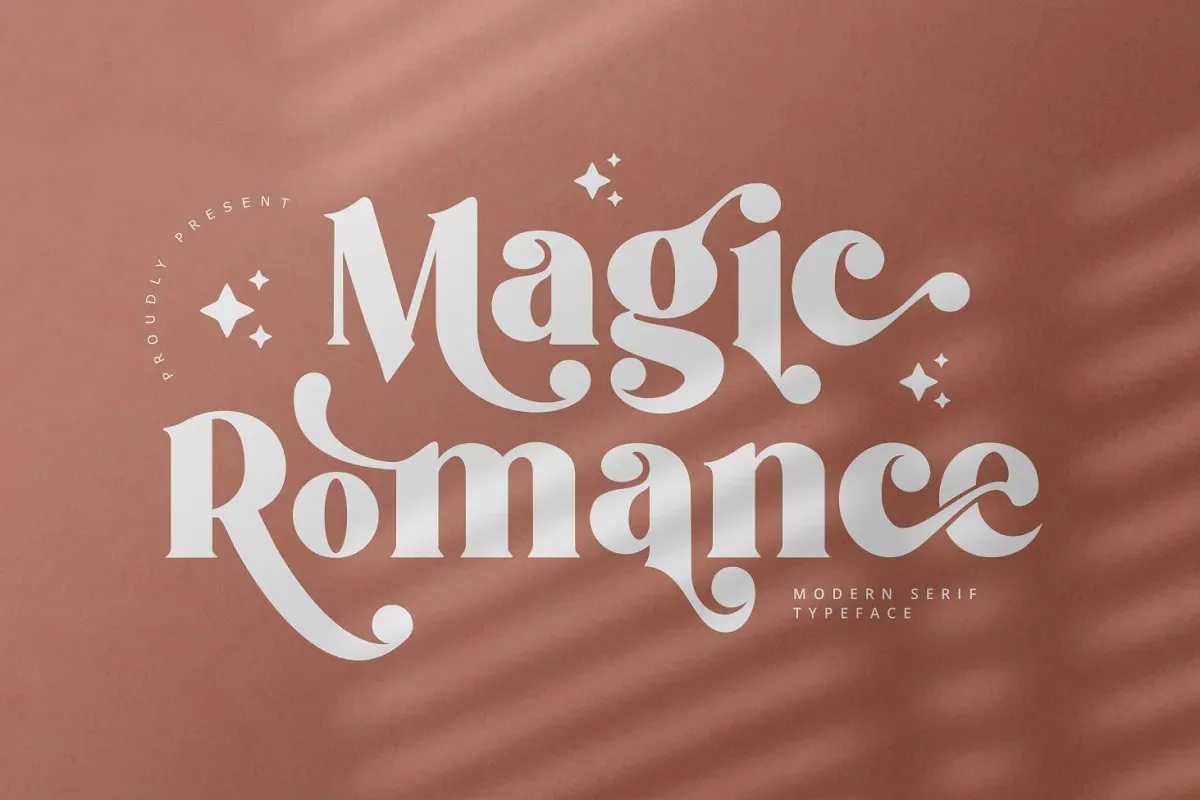
Magic Romance Font – Download Grátis
Através do site 99designs, a Zeenesia Studio nos apresenta “Magic Romance”, uma elegante fonte serif completa com todas as letras maiúsculas e minúsculas, números, pontuação e suporte multilíngue. Além disso, oferece várias ligaturas e alternativas estilísticas para personalizar ainda mais seu design. Ideal tanto para uso em logotipos como para criações de marca, embalagens, títulos e headlines, Magic Romance traz um toque sofisticado e suave que torna-a perfeita para qualquer projeto de editoração ou publicidade. Seja você designer ou criador, esta fonte não só enriquecerá seu trabalho com detalhes atraentes, mas também ajudará a destacar sua marca. Download “Magic Romance” agora e experimente uma novidade que vai deixar seu design mais sofisticado e elegante.